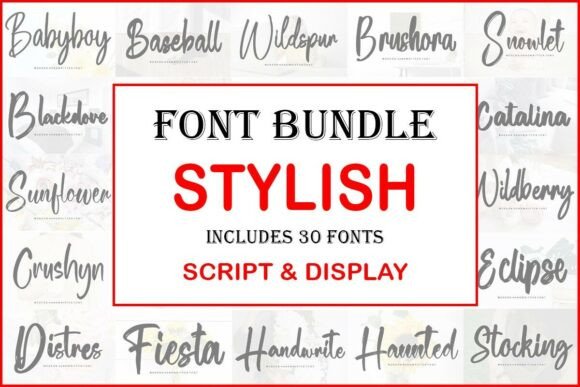
Stylish Font Bundle
適切なデザイン要素を見つけるのは難しい場合がありますが、Stylish Font Bundleは作品を即座に引き立てる優れたコレクションを提供します。
POD(オンデマンド印刷)製品、結婚式の招待状、またはソーシャルメディアのグラフィックを作成している場合でも、Stylish Font Bundleは理想的です。